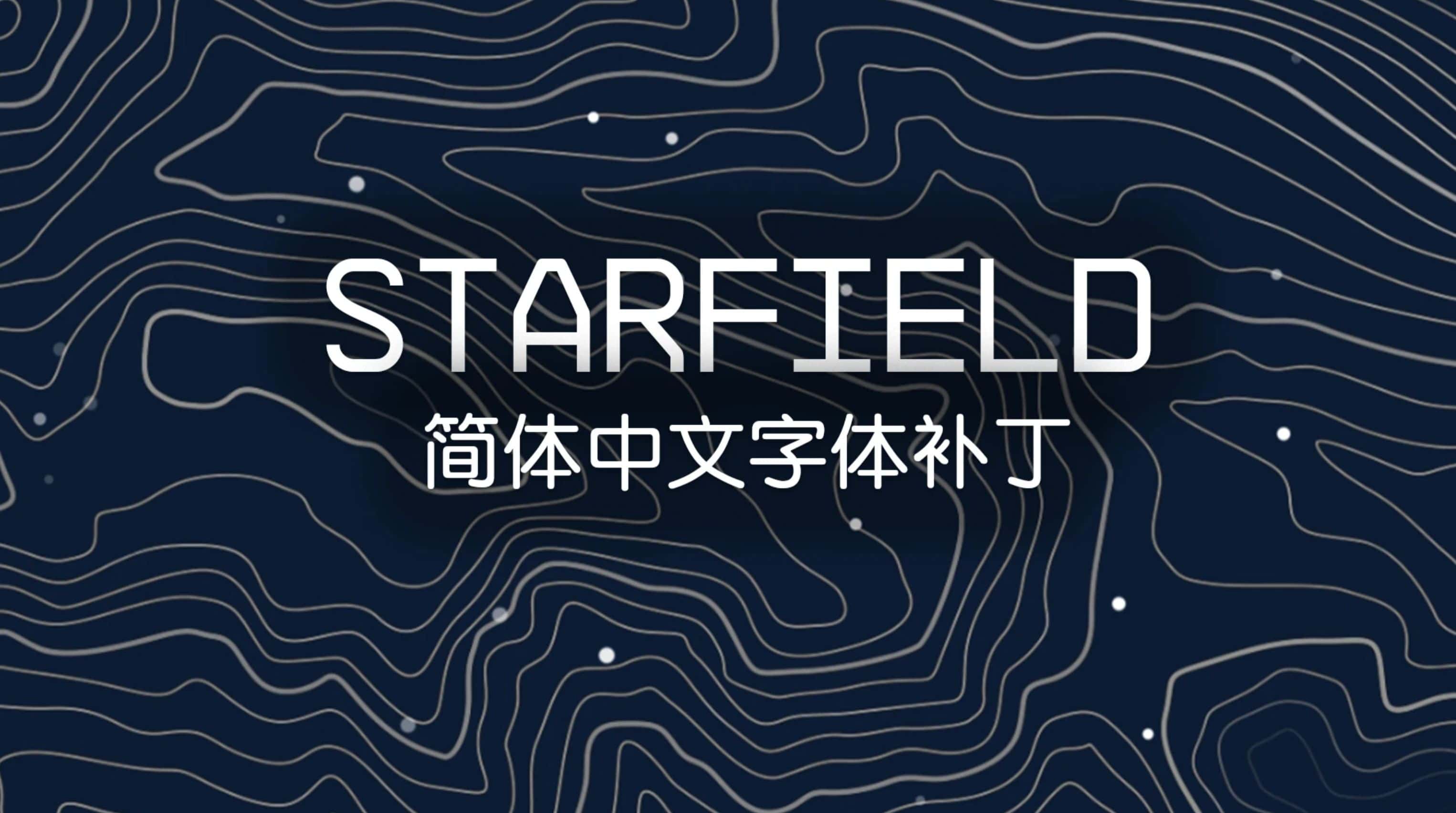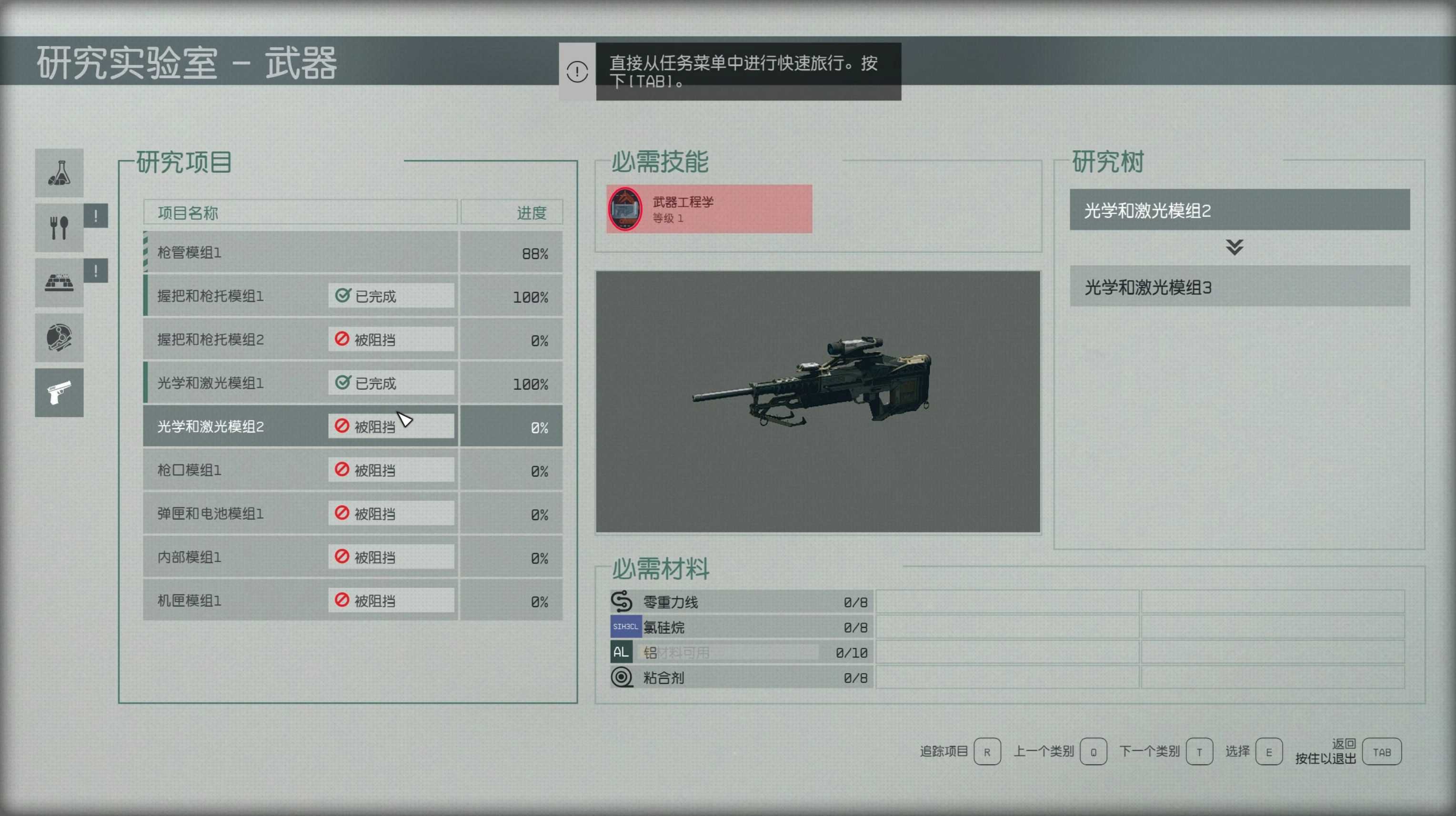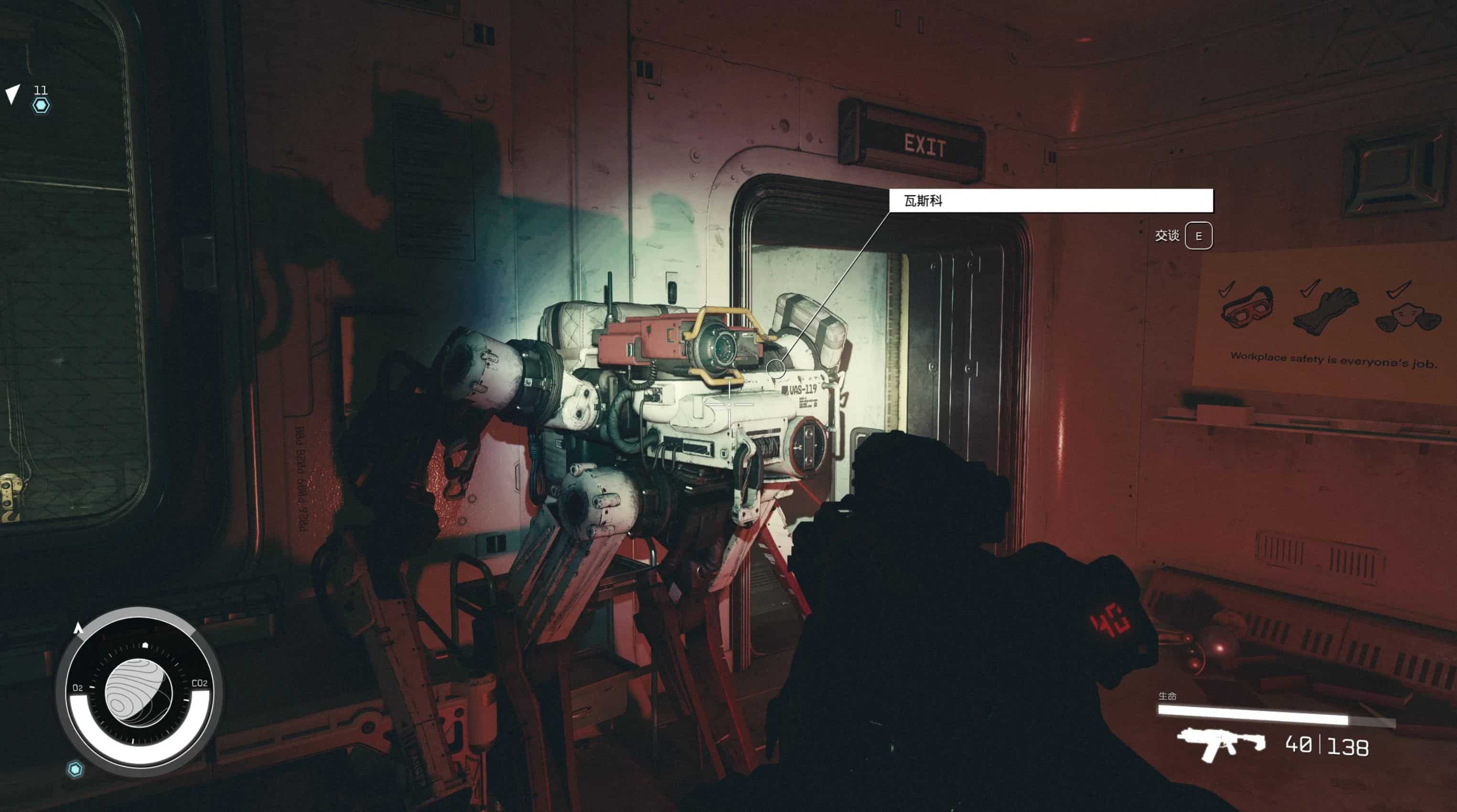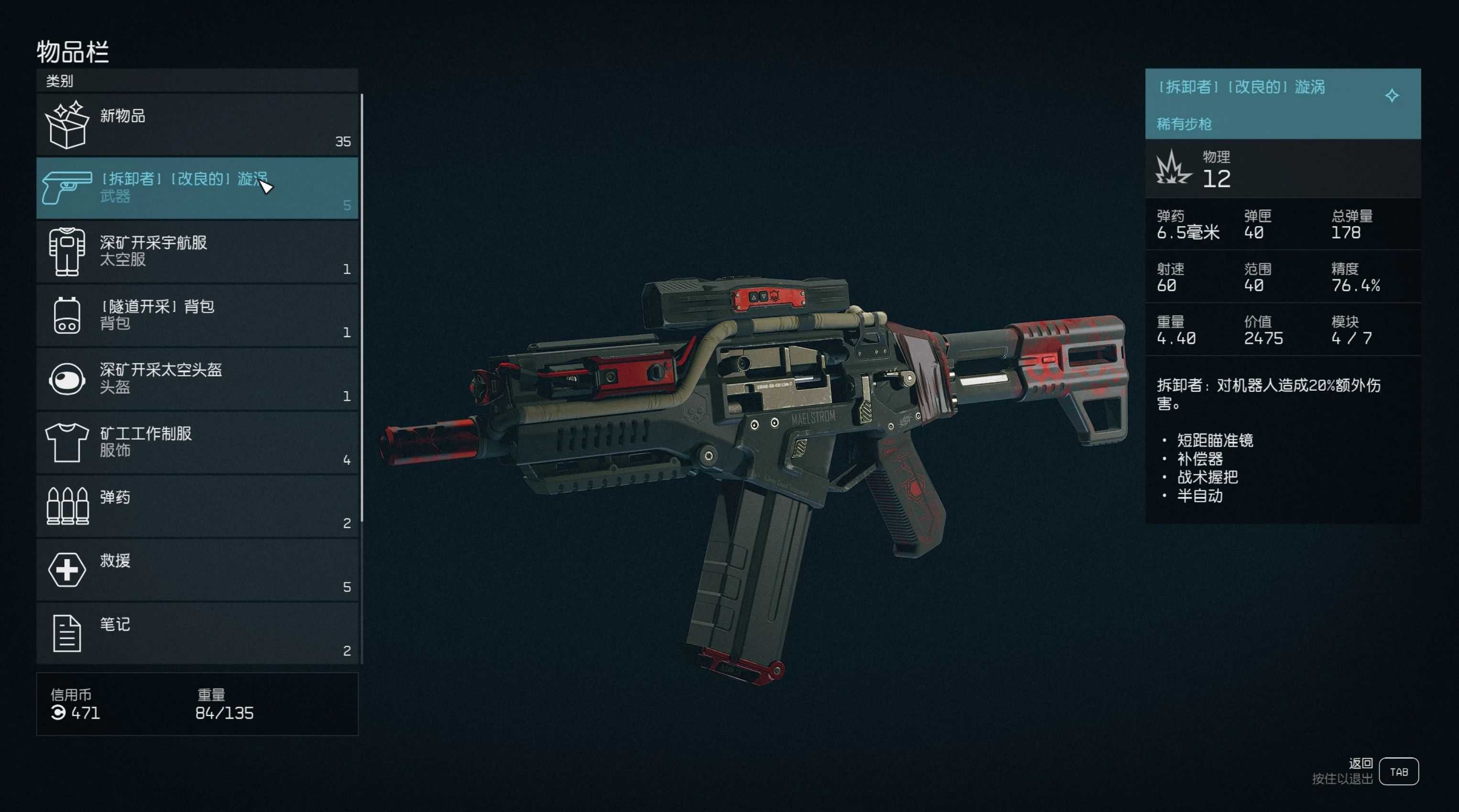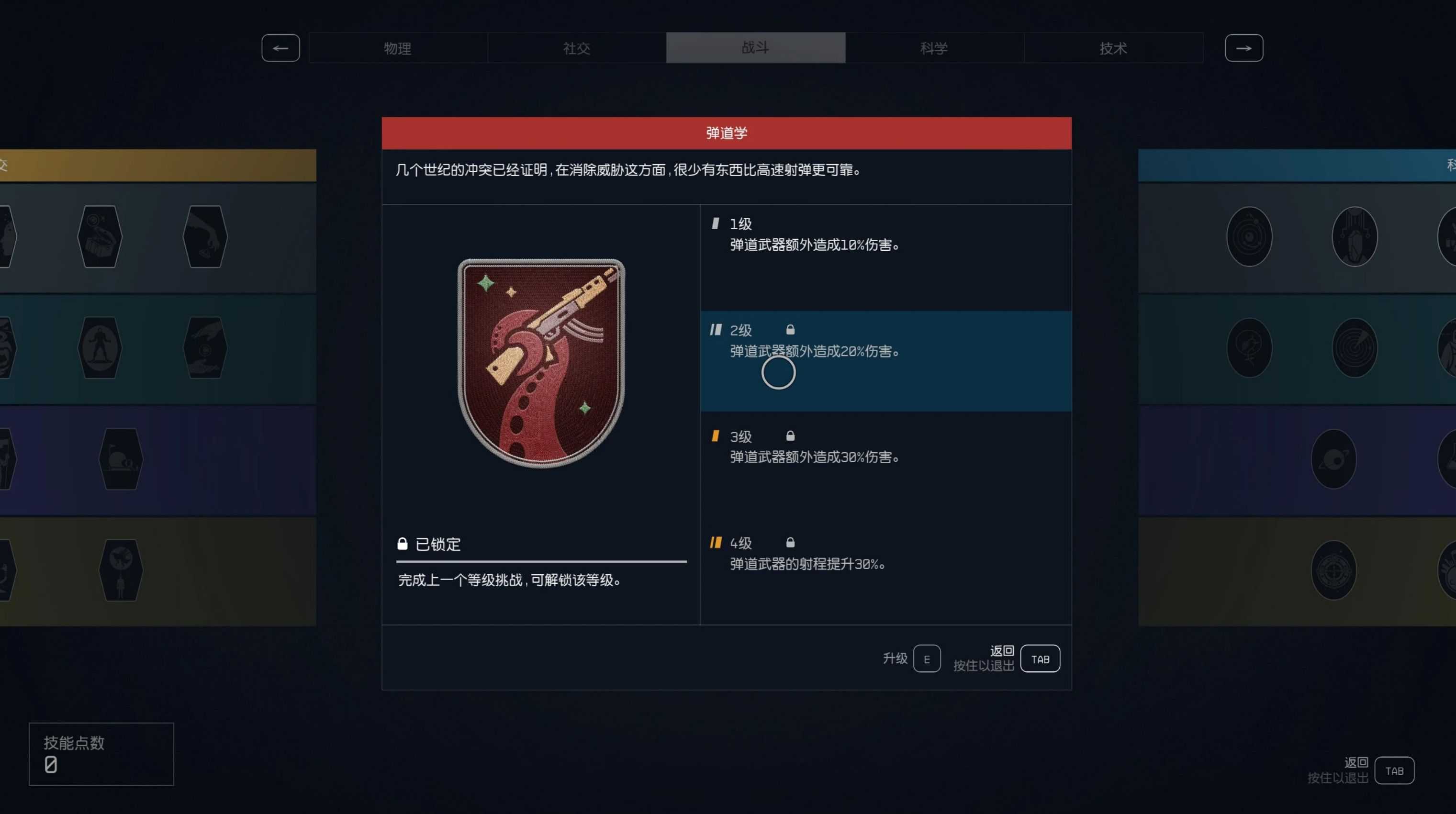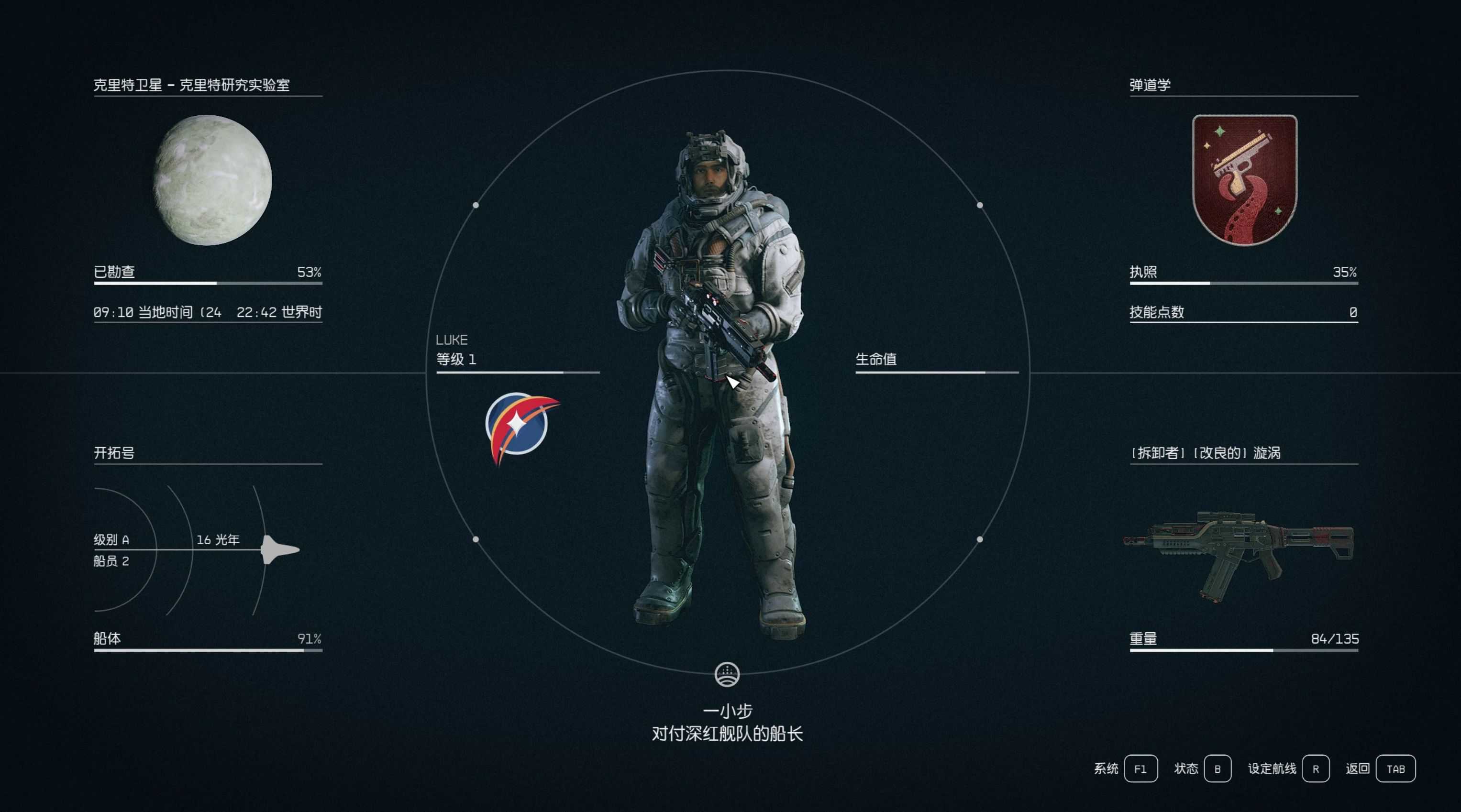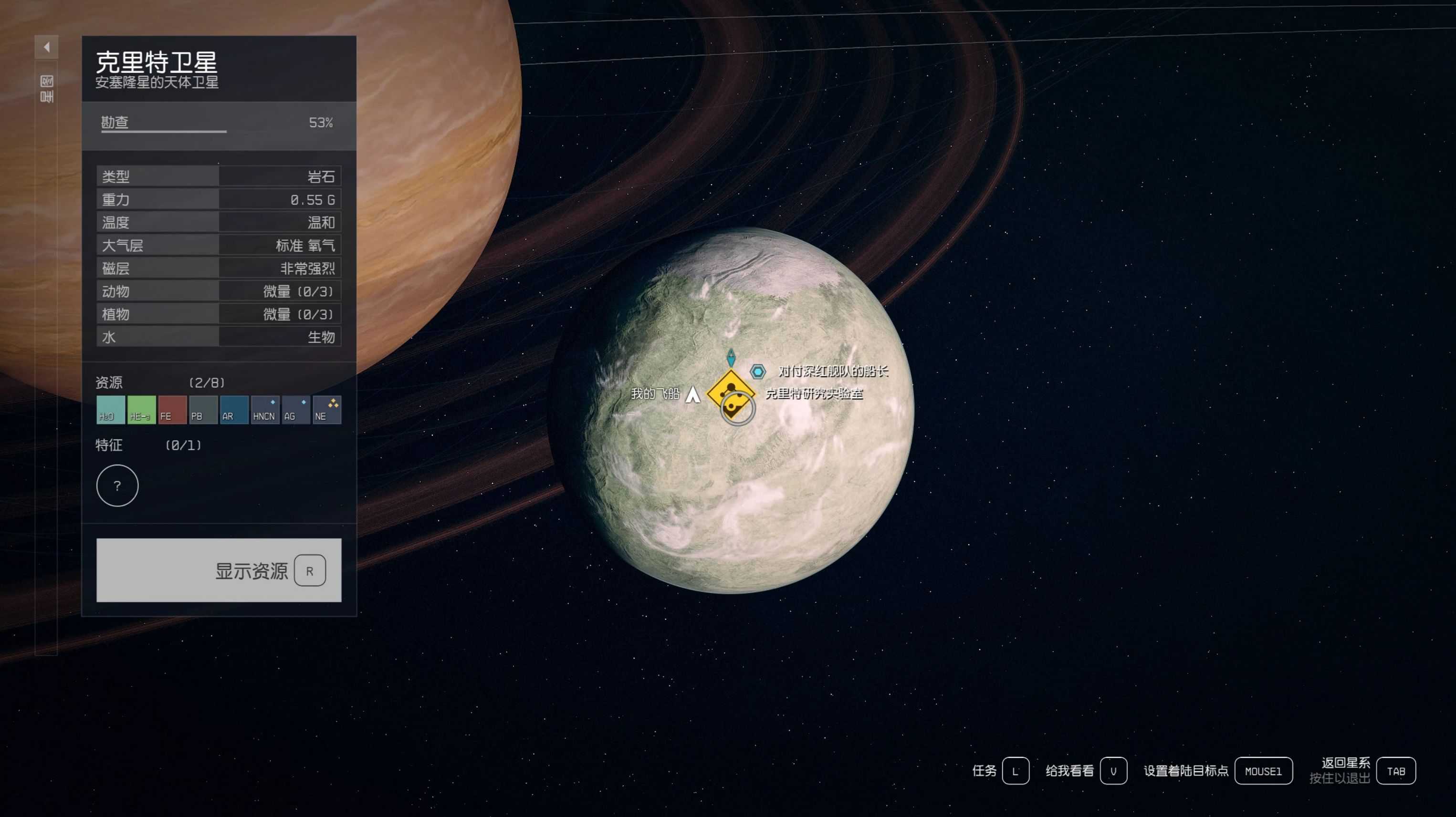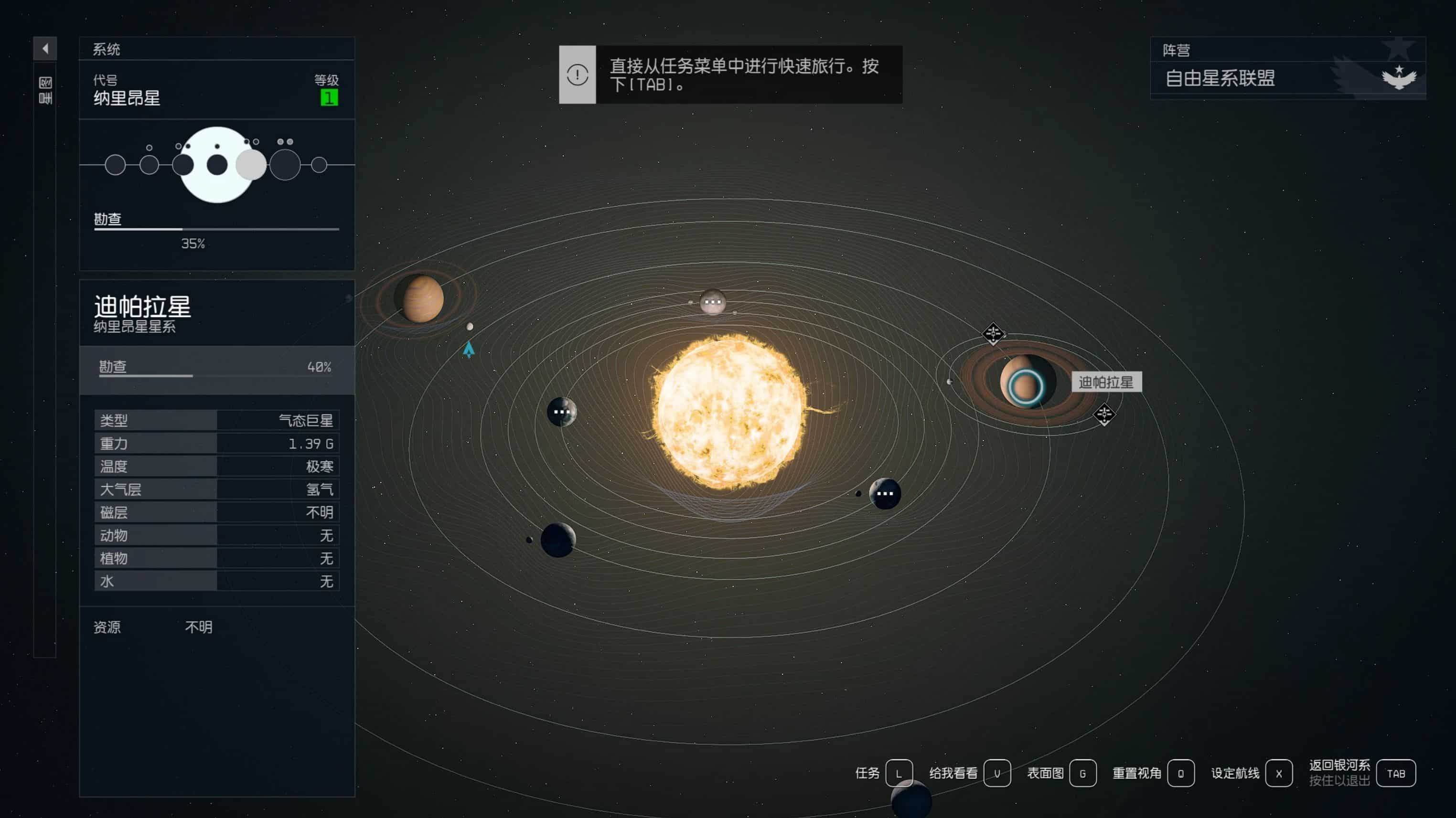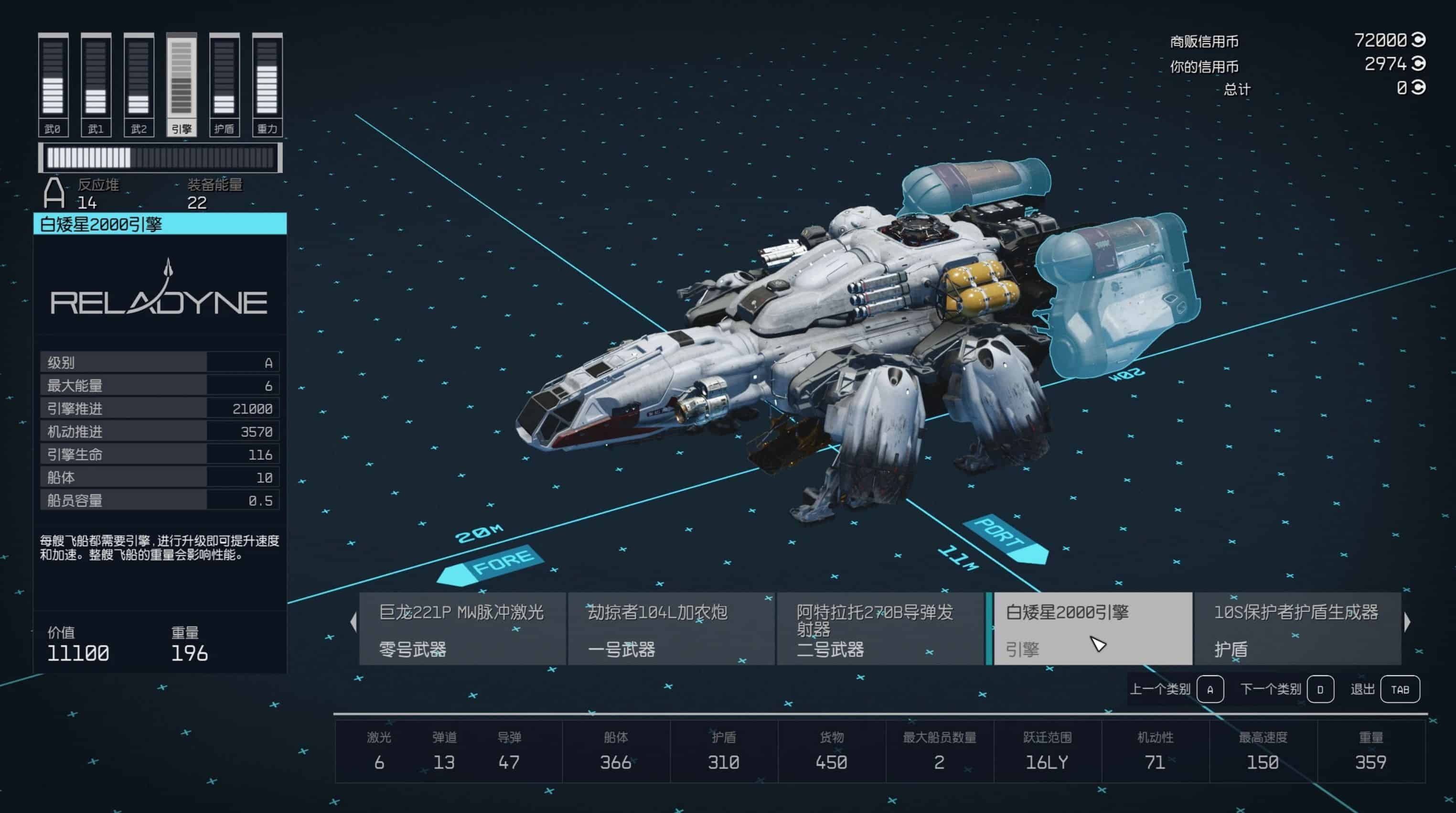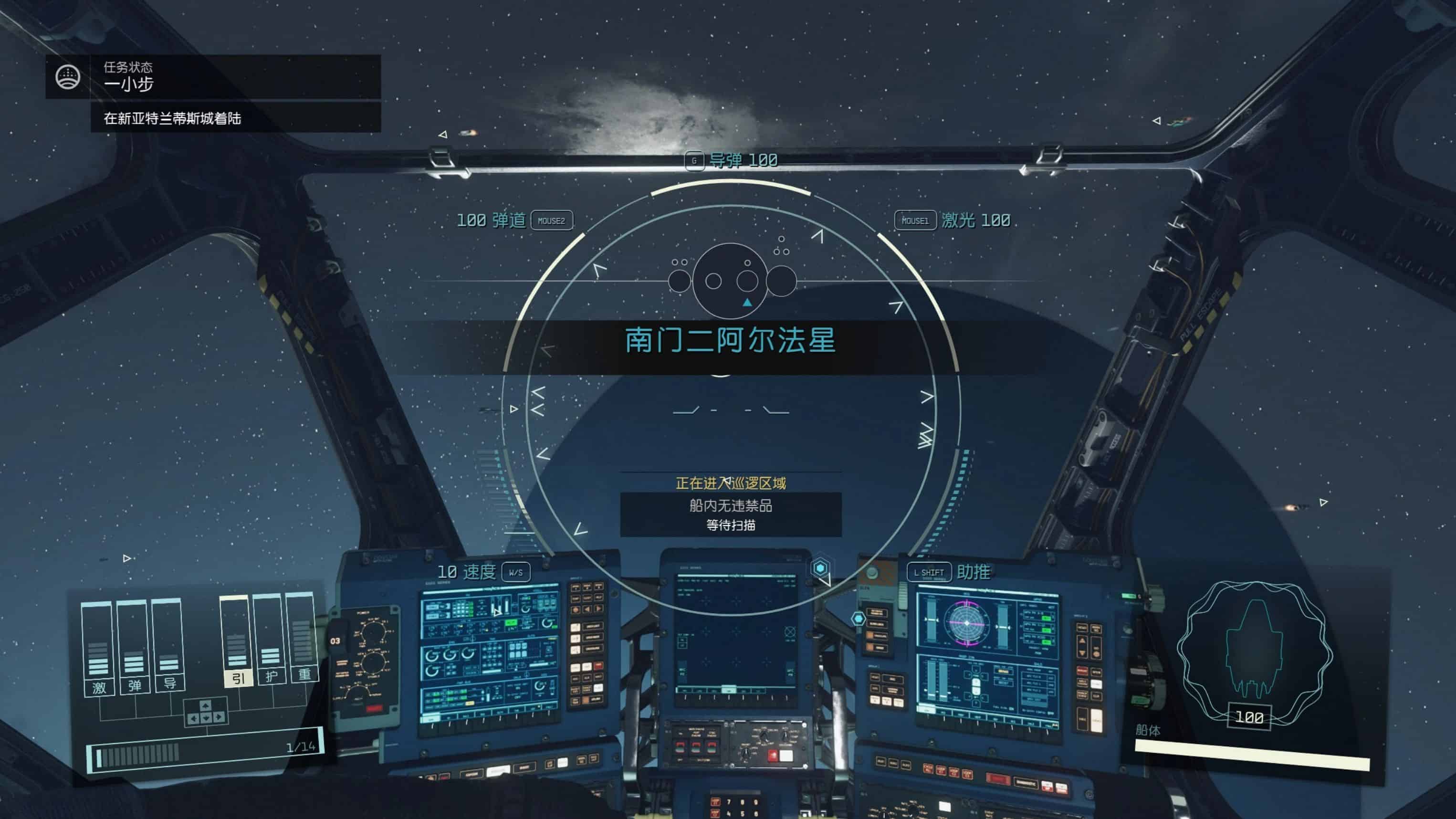
Better Fonts for Simplified Chinese
将简体中文版游戏使用的经典综艺体修改为幼圆阅读起来更清晰、友好
Modify the fonts used in the Simplified Chinese version of the game to make it clearer and more friendly to read.
同时将UI界面的大部分数字和英文内容修改为英文版字体 NB Architekt
Most of the numbers and English content on the UI interface were changed to English fonts ‘NB Architekt’.